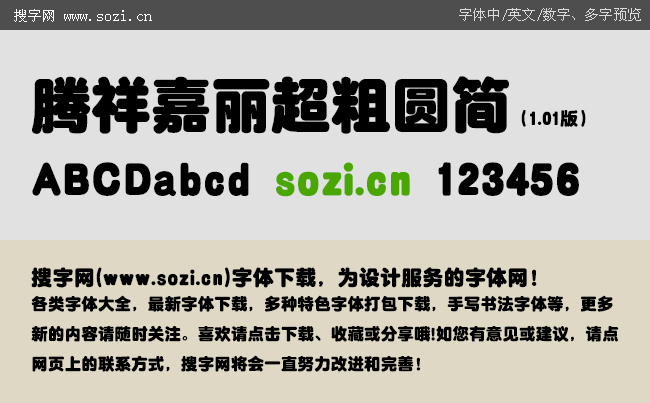
騰祥嘉麗超粗圓簡
搜字網(wǎng)提供一款騰祥嘉麗超粗圓簡字體下載,該字體每個漢字都經(jīng)過精心設(shè)計,筆畫粗細(xì)均勻、結(jié)構(gòu)美觀。每個字的圓角、圓頭、勾形都極光潔、風(fēng)格統(tǒng)一,字形放大不變形,縮小顯示清晰,適用于樣本畫冊,報紙排版,網(wǎng)頁標(biāo)題等廣告設(shè)計應(yīng)用。